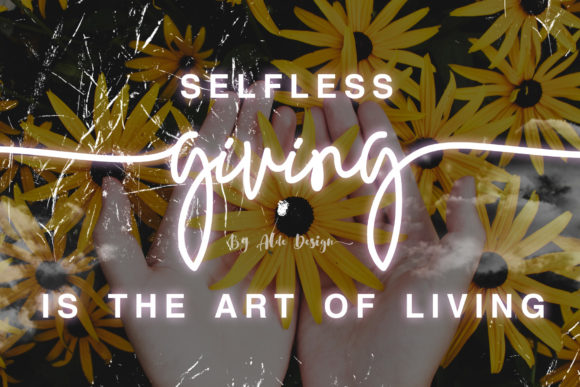
Giving Script
Giving Scriptのような高品質の素材をお探しの場合、このプレミアムパッケージはクリエイティブなプロジェクトに素晴らしい選択です。
POD(オンデマンド印刷)製品、結婚式の招待状、またはソーシャルメディアのグラフィックを作成している場合でも、Giving Scriptは理想的です。